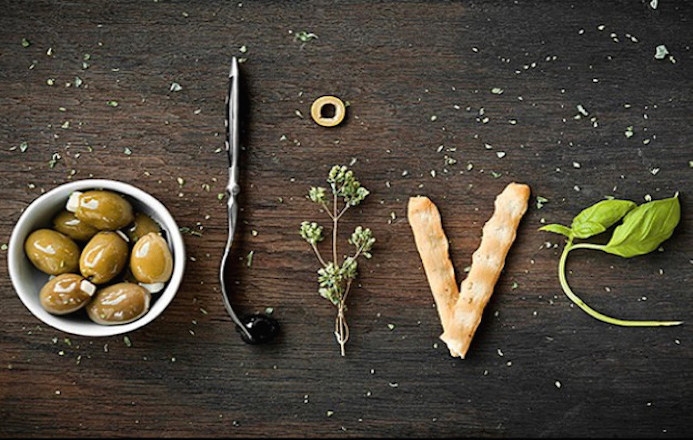
Pas besoin d'un carnet et d'un stylo pour faire de belles typographies... Quand on est aussi talentueux que Marion Luttenberg, les objets du quotidien suffisent amplement !
Olivers, bouteilles de shampoing, gouttes d'eau... Tout ce qui l'entoure est prétexte à création de typographie !
On salue la créativité et l'imagination de l'artiste et on vous laisse découvrir son travail :